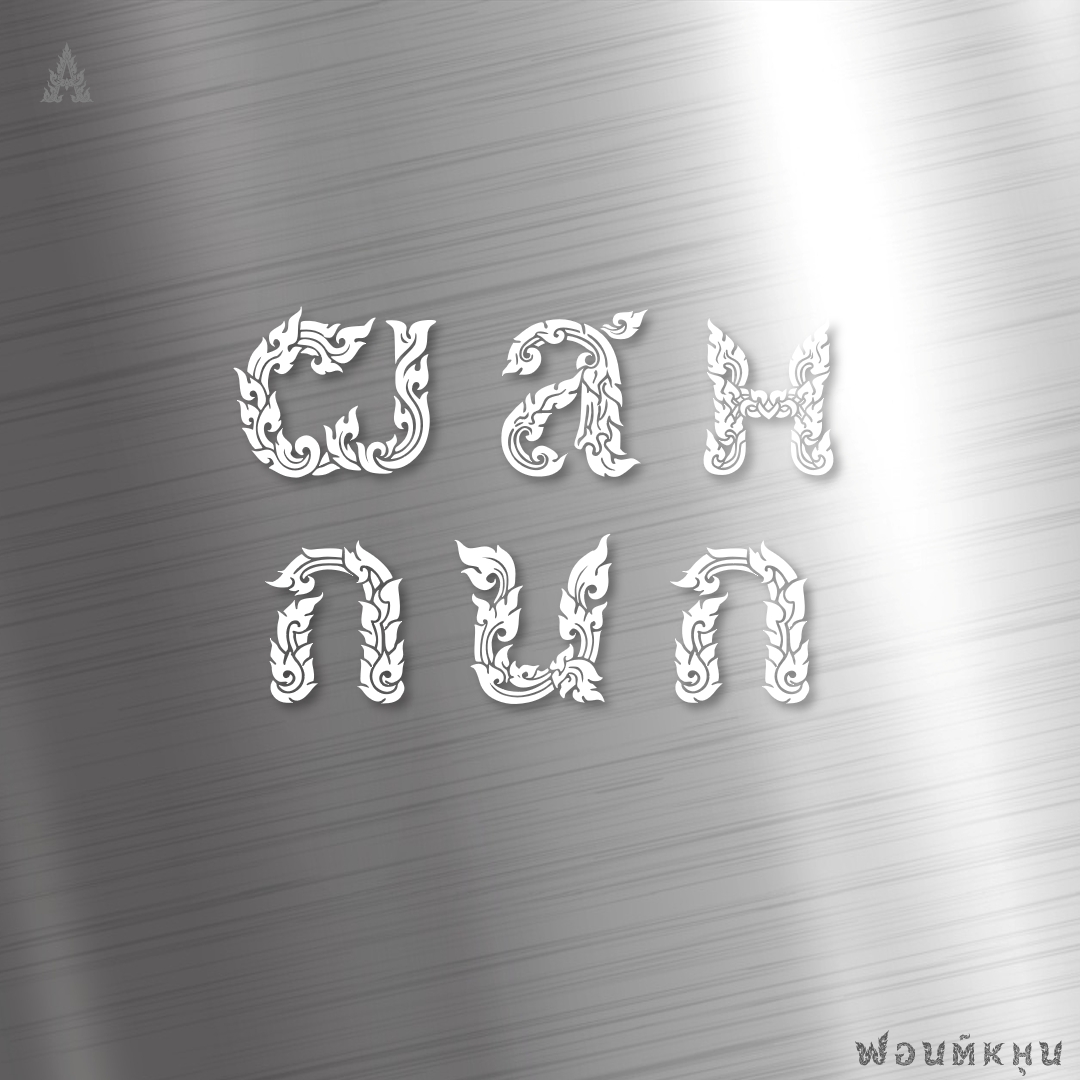
ฟอนต์ หมุน
หมุน เป็นฟอนต์ทดลองนำ AI มาช่วยงานออกแบบที่ซับซ้อน โดยให้ออกแบบลายกนก แล้วขอให้ปรับรูปร่างคล้ายตัวอักษรละติน จากนั้นก็เอามาหมุน พลิก ตะแคง ตัดแปะให้เป็นอักษรไทย
ชื่อฟอนต์ : หมุน
หมุน เป็นฟอนต์ทดลองนำ AI มาช่วยงานออกแบบที่ซับซ้อน โดยให้ออกแบบลายกนก แล้วขอให้ปรับรูปร่างคล้ายตัวอักษรละติน จากนั้นก็เอามาหมุน พลิก ตะแคง ตัดแปะให้เป็นอักษรไทย
เบื้องหลังนิดหน่อย
ณ วันที่ AI ทำได้ทั้งลายไทย และอักษรไทย  ก็เลยขอให้ออกแบบอักษรไทยลายไทย (ดังรูป)
สำหรับคนทั่วไป.. อืม!!สวยดี เก่งมาก
สำหรับคนใช้ฟอนต์ คนสร้างฟอนต์.. เอ๊ย!!นี่มันฟอนต์ XXXXX นี่
ดังนั้น จึงต้องหาวิธีอื่น..  จะให้ออกแบบอักษรละตินเป็นลายไทย ก็จะได้ เอ๊ย!!นี่มันฟอนต์ XXXXX นี่ เหมือนกัน
ก็เลยปรับเป็น ให้ออกแบบลายไทยก่อน  จากนั้นค่อยบอกให้เปลี่ยนรูปทรง คล้ายอักษรละติน เช่น I J K U O n u .. คราวนี้จะได้ ลายไทยเป็นเส้นคล้ายเส้นรูปแบบต่างๆ
แล้วค่อย เอามาหมุนๆ หรือตัดแปะรวมร่างให้คล้าย อักษรไทย
ใช้เวลาดราฟต์กี่เดือนครับนี่ :55:
ไปค้นดูรูปที่เป็น first draft ก็ประมาณ ปลาย พฤศจิกา ครับ
ตอนนั้นกำลังเลือกทางให้ฟอนต์หนักหน่วง ว่าจะใช้เส้นแบบ metal (รากไม้) หรือทำเป็นลาย กนกไฟ ดี  ก็เลยให้ AI gen รูปกนกไฟแบบต่างๆให้ แต่มันไม่เข้าเค้า
เลยเอารูปที่ใช้สร้างฟอนต์ บอกทาง (อักษรทางหลวง) มาเป็นแบบ ผลที่ได้ ดังรูปด้านบน (ได้แต่ร้อง เชี่ย!!! ในใจ)  จากนั้นก็ไม่สามารถ gen รูปแบบนี้ได้อีกเลย 55
พอดี nano banana pro ออกมาช่วงนั้น.. ก็เลยไป ดูแนวทางอื่นๆพักใหญ่ กว่าจะกลับมาใช้แนวทางเดิม ก็กลางเดือนธันวา ครับ
หมายเหตุ ถ้าดูดีๆ มันเป็นงานละเอียด ที่หยาบครับ มีจุดต้องแก้ไขเยอะมาก AI เป็น first draft ที่ดี ร่างเส้นที่เราไม่คิดว่าจะทำ ใช้เวลาหาแนวทางในการกำกับ AI จริงๆประมาณ 2-3 วันก็เสร็จ ..แต่ถ้าเก็บงานจริงๆ คงอีกหลายเดือนเลย